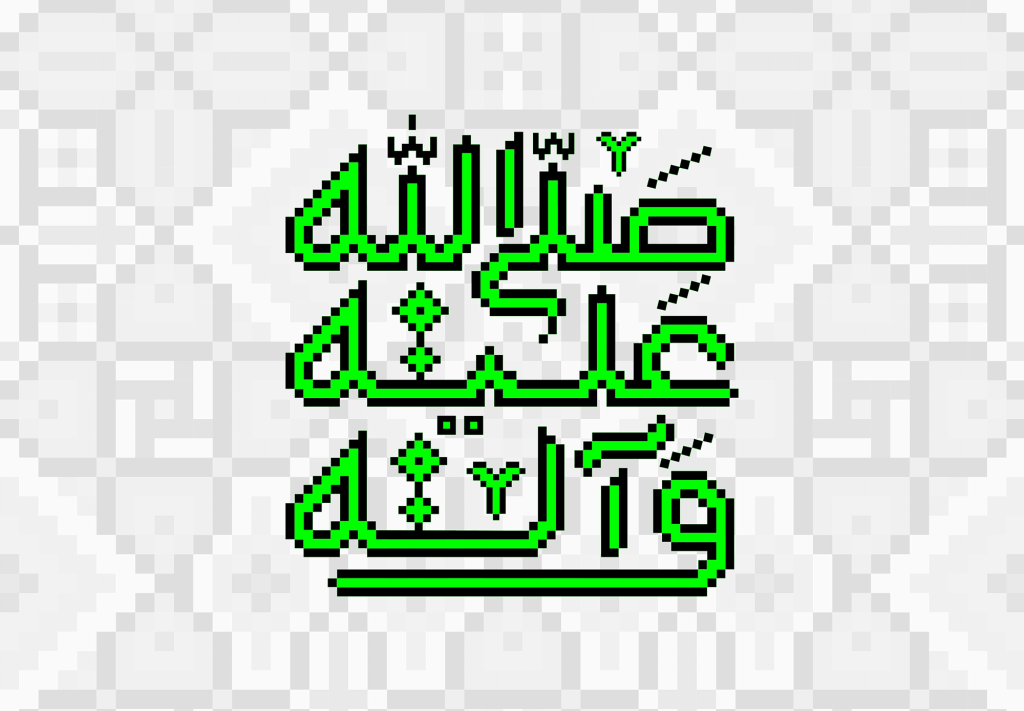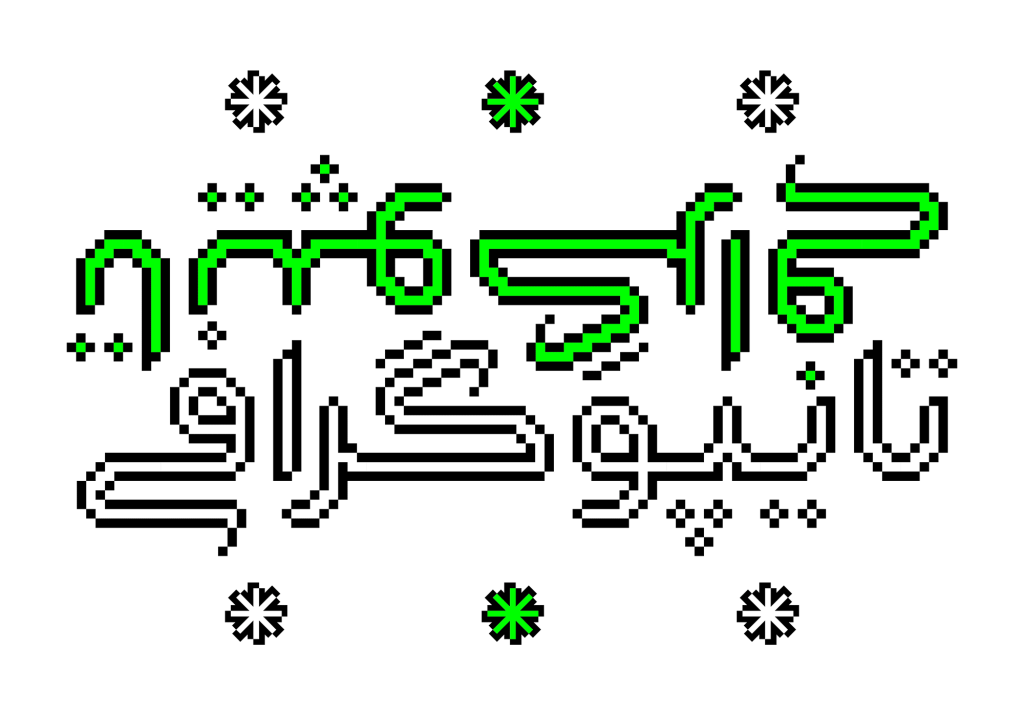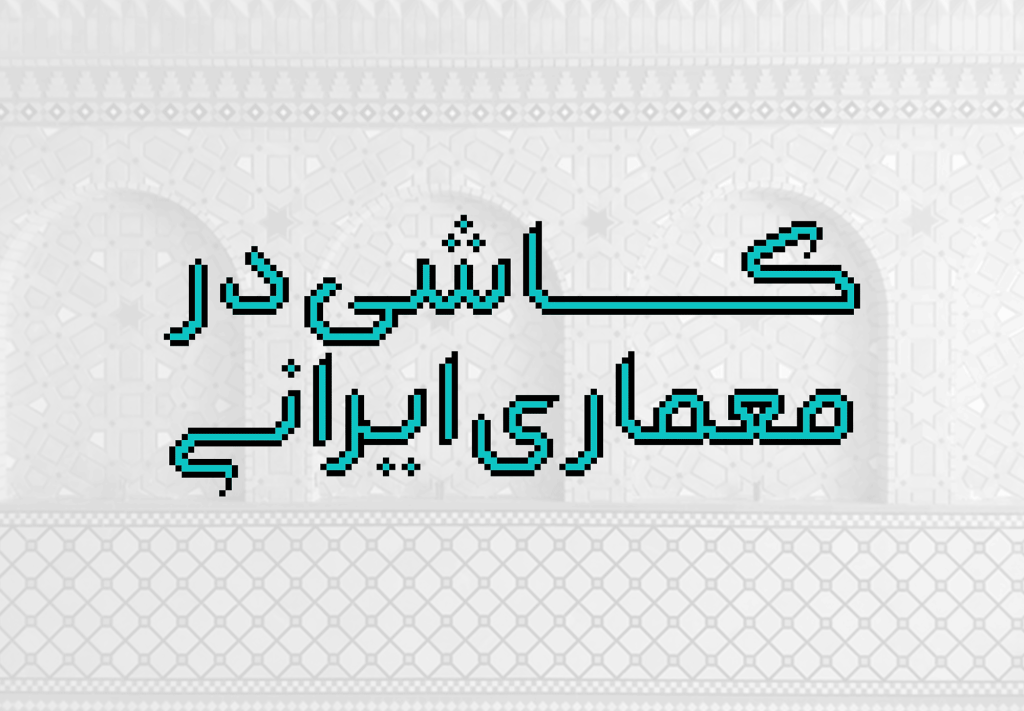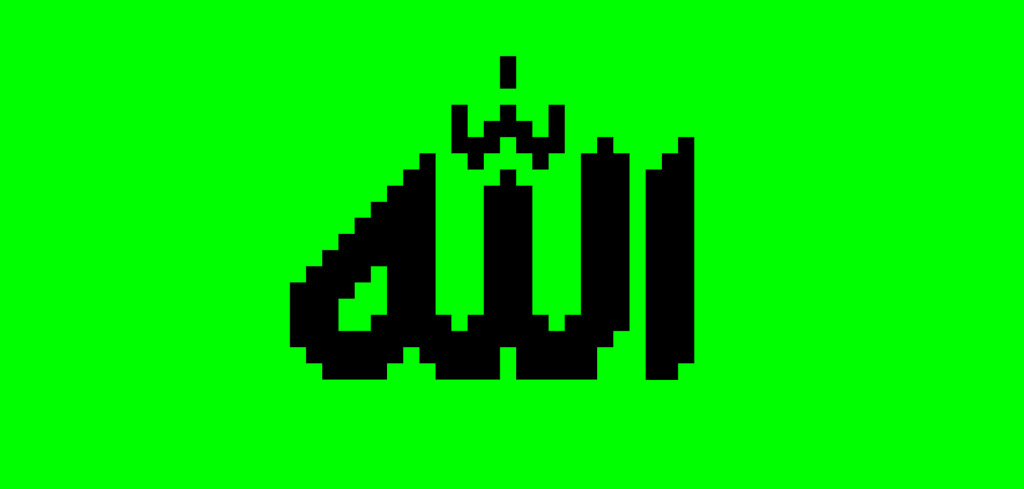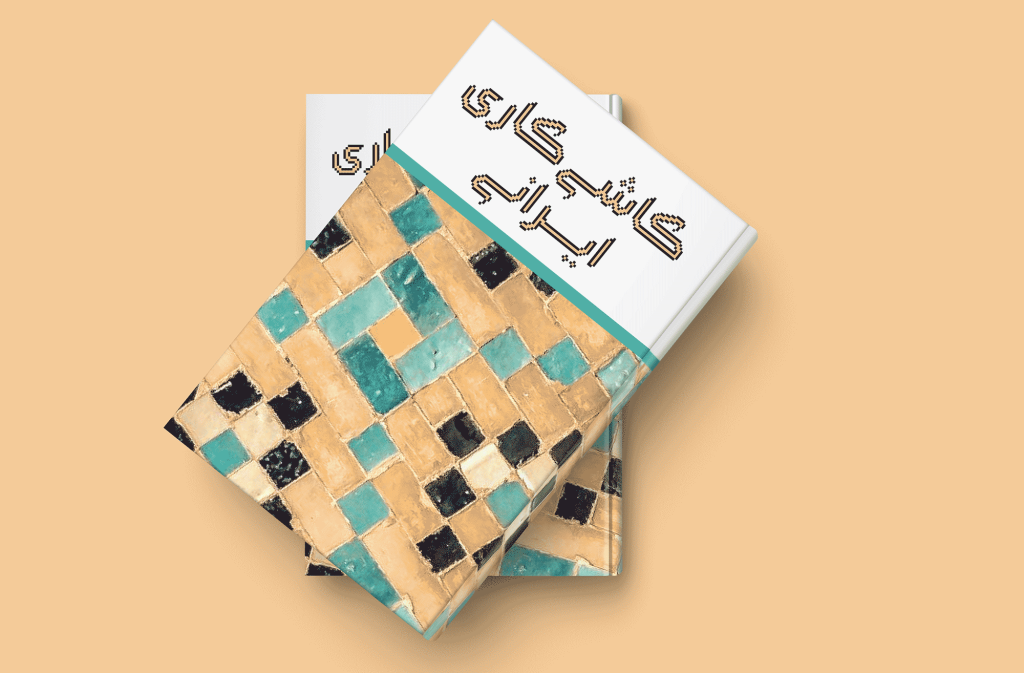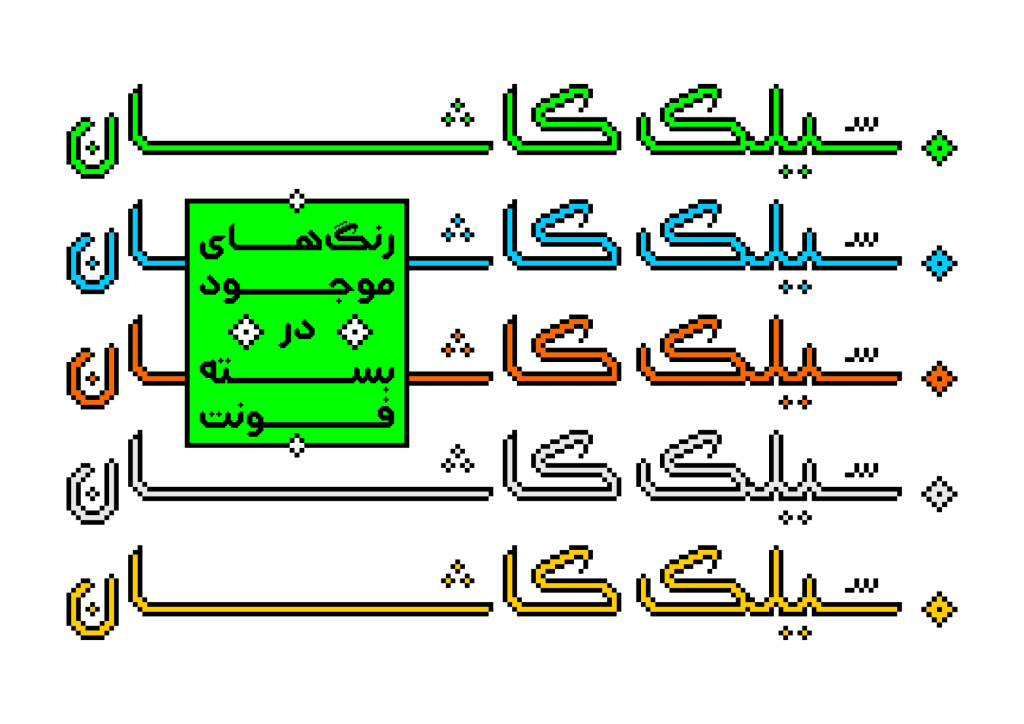
فونت گلچین
فونت گلچین بر اصل و اساس خطوطی چون کوفی،ثلث، و بعضاً سایر اقلام خوشنویسی نقش بستن بر شبکه ای شطرنجی است که این قلم از همین قائده الهام و قدم به عرصه وجود نهاده است. شایان ذکر است قوانین رسم آن با سایر نمونه ها اندکی متفاوت است.( گونه شناسی خط بنایی (معقلی)، بر اساس شیوۀ طراحی و روش های اجرایی،حمیدرضا کشاورزی میاندشتی،بهمن فیزابی)
گلچین شکل امروزی شده و کاربری خط ساقه گنبدی است.
خط ساقه گنبدی نوعی برخورد مینیمال با طراحی حروف است. طراحی حروف پیچیده فارسی با منحنیهای زیاد در یک شبکه محدود شطرنجی کاری بسیار مشکل است. فونت رنگی گلچین در پنج رنگ
وحید یعقوبلو در طراحی و خلق تایپفیس گلچین محدودیتهای بیشتری نیز برای رعایت سیستم حروفچینی در فونت داشته است. حل این مشکلات منتج به طراحی این محصول شده است که در ادامه میتوانید ببینید و فونت آن را خریداری کنید.